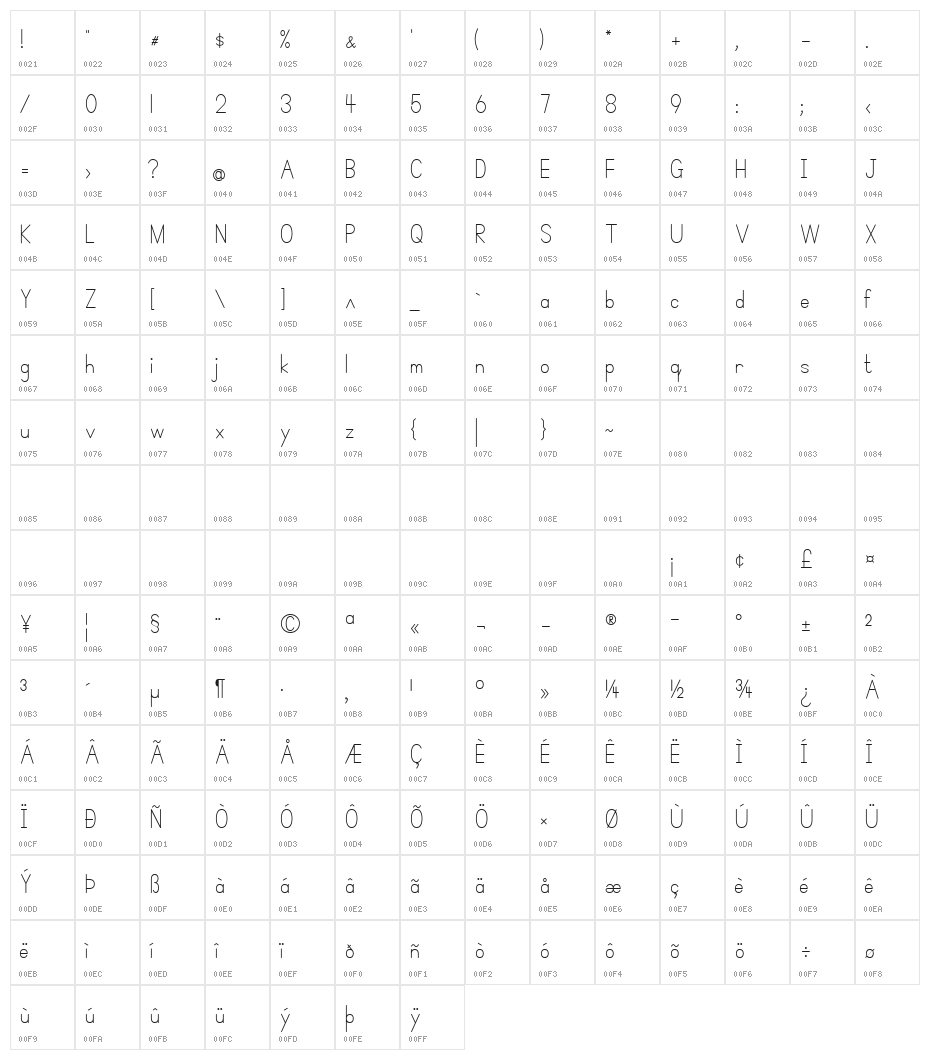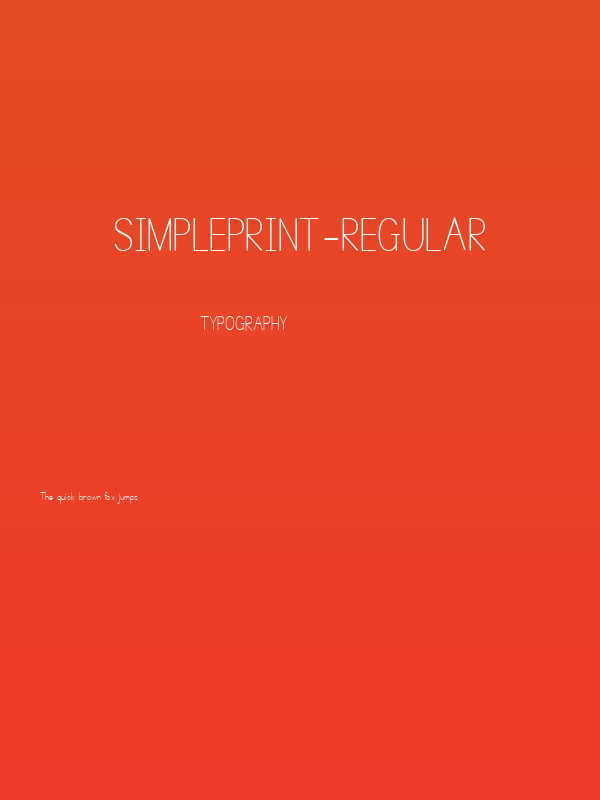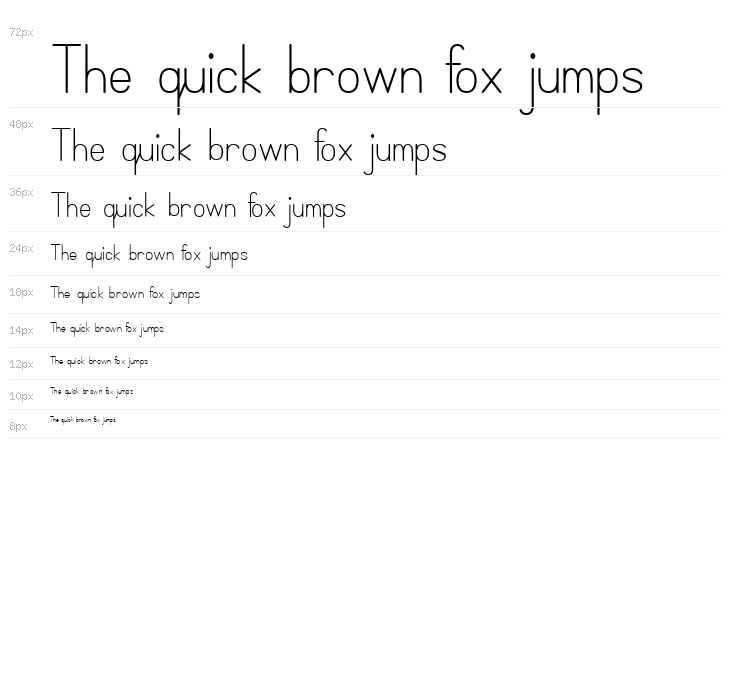
SimplePrint-Regular Font
| Progetti proposti | Ideal for minimalist branding, modern web design, clean editorial layouts, and simple product packaging. |